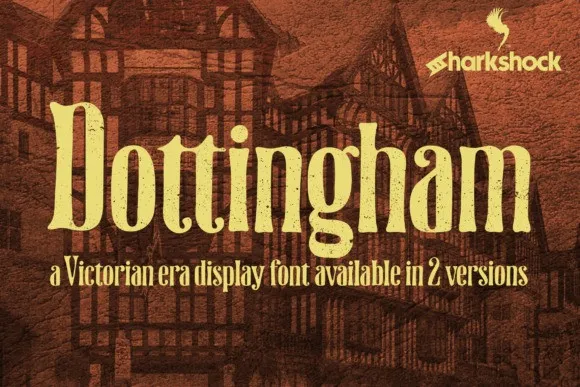
Esta fonte foi criada por Sharkshock, inspirada na arte antigamente feita a mão nas placas de sinalização. Ela foi desenhada à mão e tem um design único para cada letra, resultando num tipo poderoso que se encaixa em uma ampla gama de criações que exigem um toque distinto. Ideal para quem busca um acabamento chamativo e diferente, a Dottingham Font traz uma atmosfera vibrante que combina bem com designs de estilo display. Seja você um designer gráfico ou criador de conteúdo digital, essa fonte estará à sua disposição como uma escolha versátil para dar seu trabalho aquecimento único.